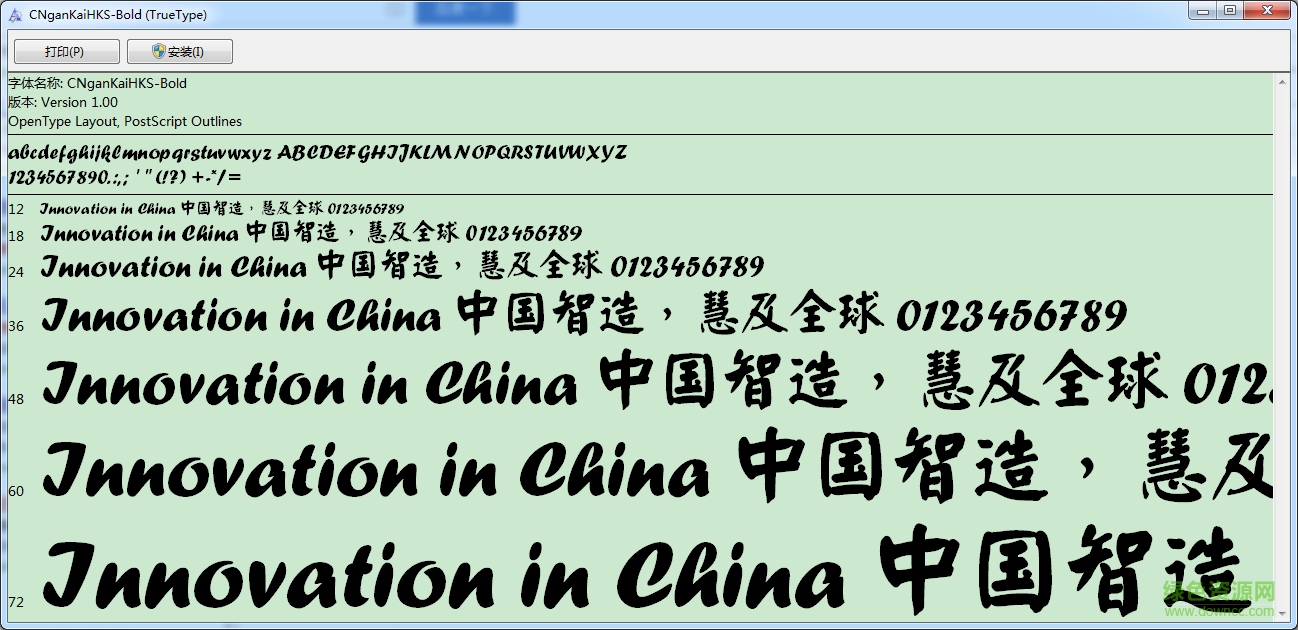
蒙納簡(jiǎn)顏楷體是一款非常漂亮的簡(jiǎn)體字體,這款字體大氣沉穩(wěn),筆畫上處理精致得當(dāng),十分美觀,整體效果非常出色,比較適用于廣告設(shè)計(jì)、美術(shù)設(shè)計(jì)等領(lǐng)域。喜歡這款自提的朋友歡迎來(lái)綠色資源網(wǎng)下載使用!